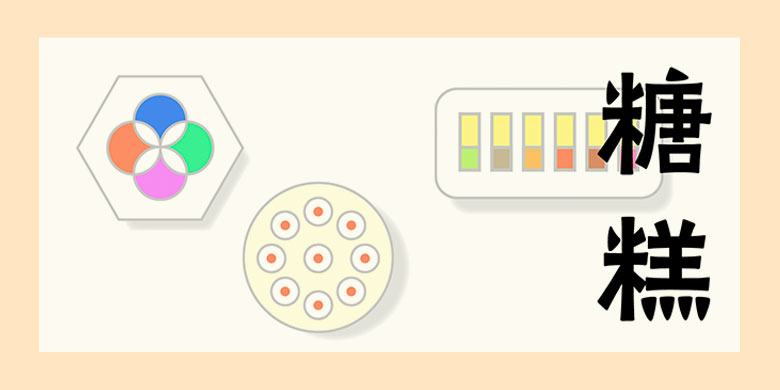
方正铭石体
方正铭石体,这款字体结构工整、笔画清晰,兼顾美观与易读性,适用于标题、正文、海报、包装、LOGO 等多种场景。字形优雅稳定,风格百搭耐看,适配日常排版与创意设计,让文字呈现更舒适、更具质感。方正铭石体一笔一画,皆是细节,以均衡的比例、流畅的线条打造舒适视觉体验,字形端正大气,风格简约现代。无论是商业设计、品牌宣传还是日常排版,都能轻松驾驭,让文字更有格调与力量。方正铭石体字体下载。
字体品牌: 方正字库设计师:今田欣一 字体分类:创意字体 字体属性:精品字 字符集:大陆简体(GB2312-80) 发布时间: 2019
方正铭石体,中国晋代墓志铭所用隶书被称为铭石体,典型例子为《王兴之墓志铭》,这种铭文的外形,也许在制作时增加了些许雕刻的细节,使其风格与现代的黑体字极为接近。《王兴之墓志铭》全称《王兴之夫妇墓志铭》,是一块墓石,这块石头两面刻字,即分别刻夫妇两志。一面刻于东晋咸康六年(公元340年);另一面刻于永和四年(公元348年),碑文共计203字。《王兴之墓志》书法封着端整,字体的介于隶楷之间,平整均匀,接近楷书,简化了隶书的一些波磔挑脚。中文部分为铭石体,西文部分为“K.E.Sagittarius”,方正铭石体是一款组合而成的综合书体。